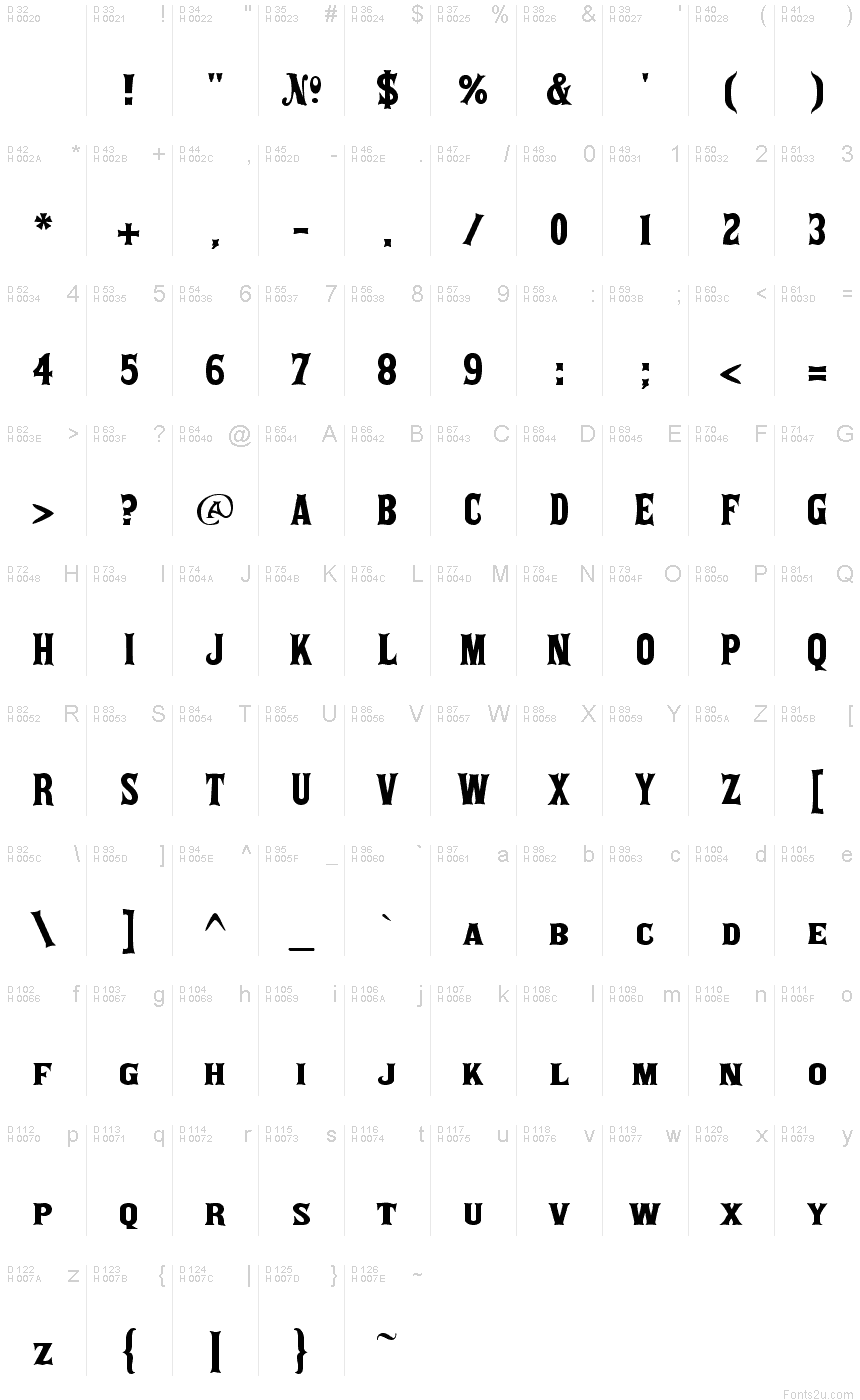
由 James Milligan 和 akaType 设计的 akaPosse 是一款免费的复古展示字体,带有狂野西部酒馆的独特豪迈感。其厚实的笔画、富有张力的曲线和紧凑的节奏,赋予了它那种西部电影海报的复古尘土感,同时略微收紧的比例使其看起来既扎实又有冲击力。这是一款从牛仔竞技海报中直接走出来的字体——大声、沉稳且充满个性。
使用 akaPosse,你的标题瞬间就会充满活动感:无论是酒吧招牌、烧烤或牛仔竞技海报、音乐传单、主题菜单、复古品牌设计还是游戏标题,都能从它那不羁的魅力中受益。这款免费字体非常适合在大字号下使用,让它厚重的笔画尽情展现。在正文排版中,建议搭配一款干净、不突兀的无衬线字体,让 akaPosse 负责把控格调,而辅助文本则保持简洁,互不干扰。